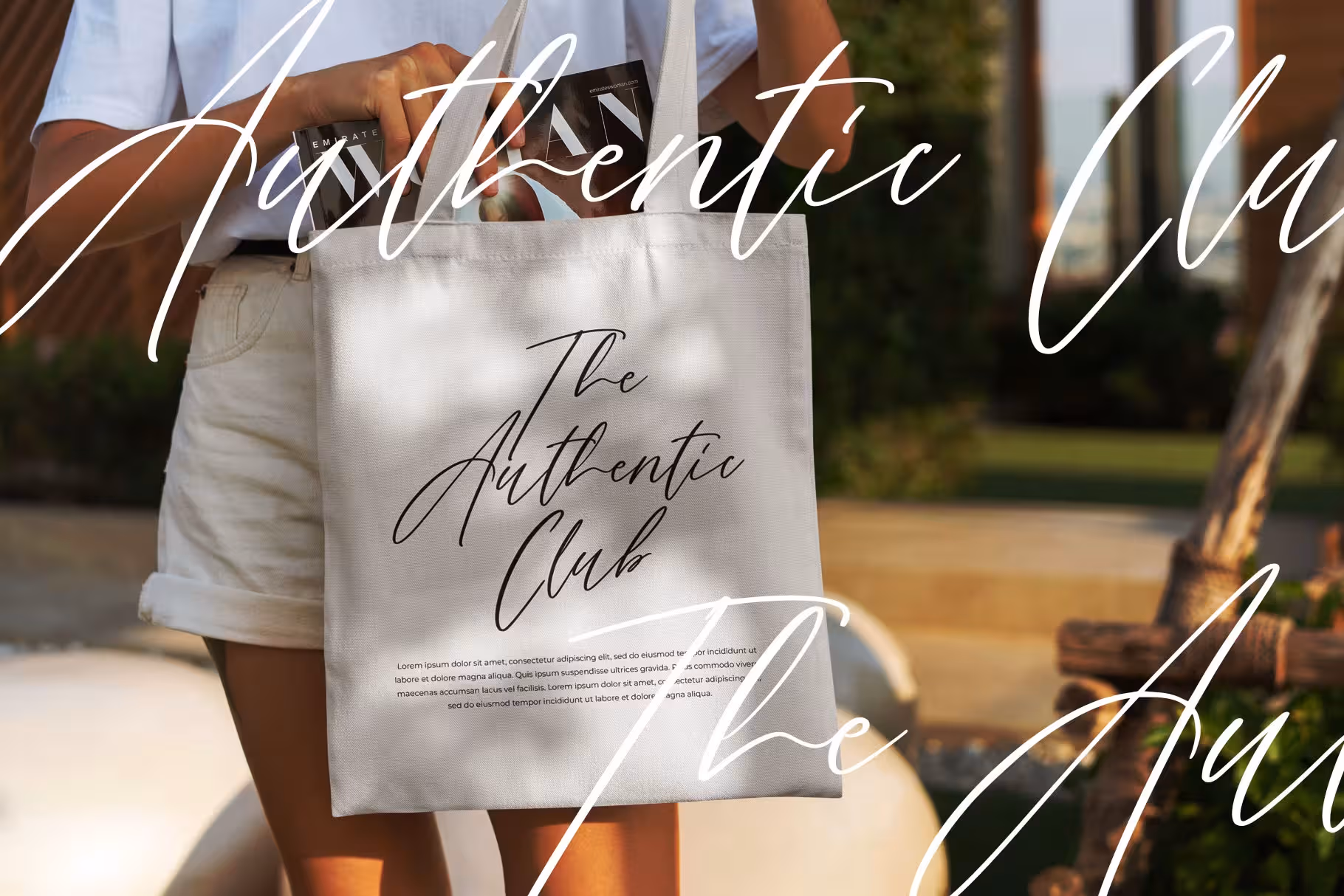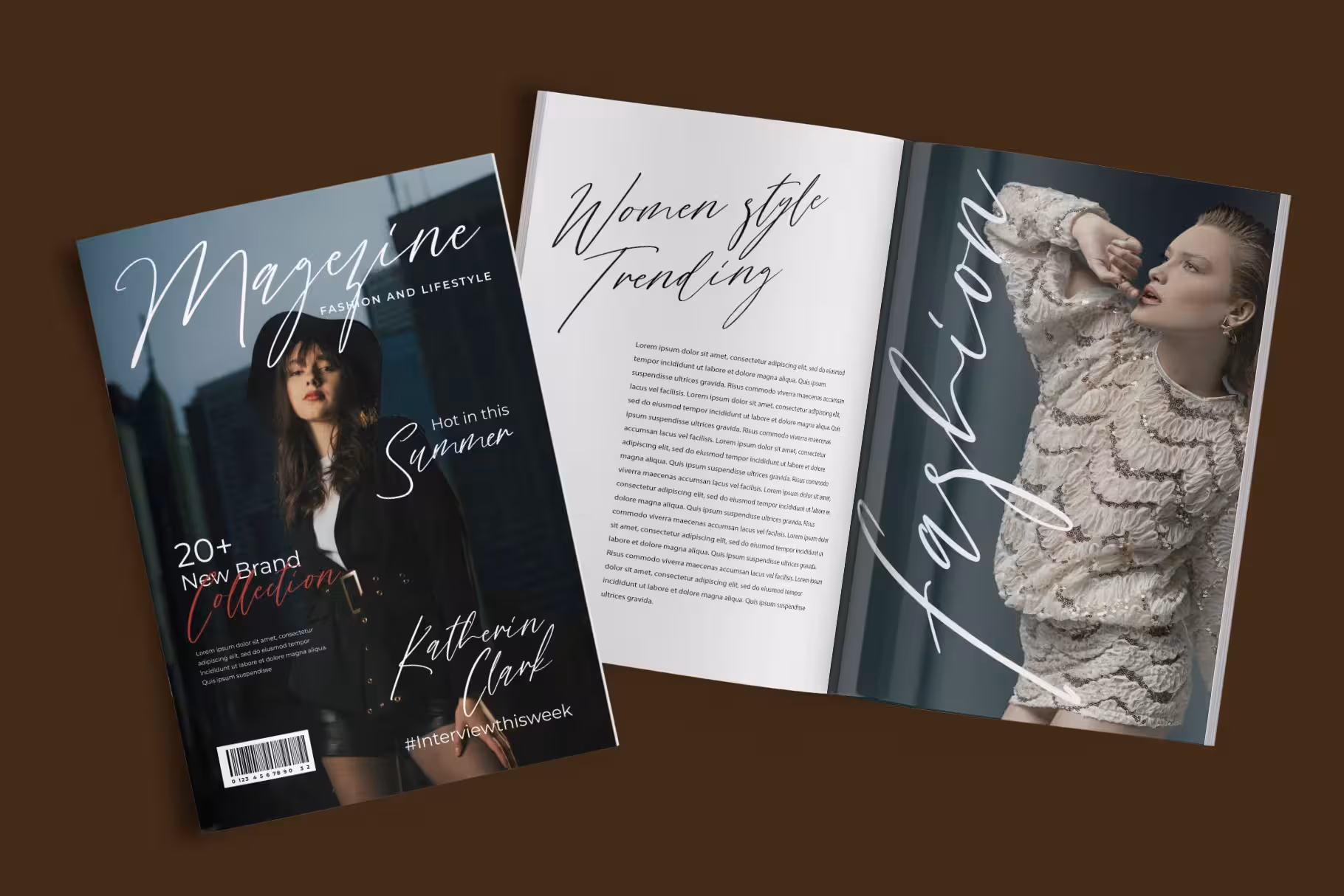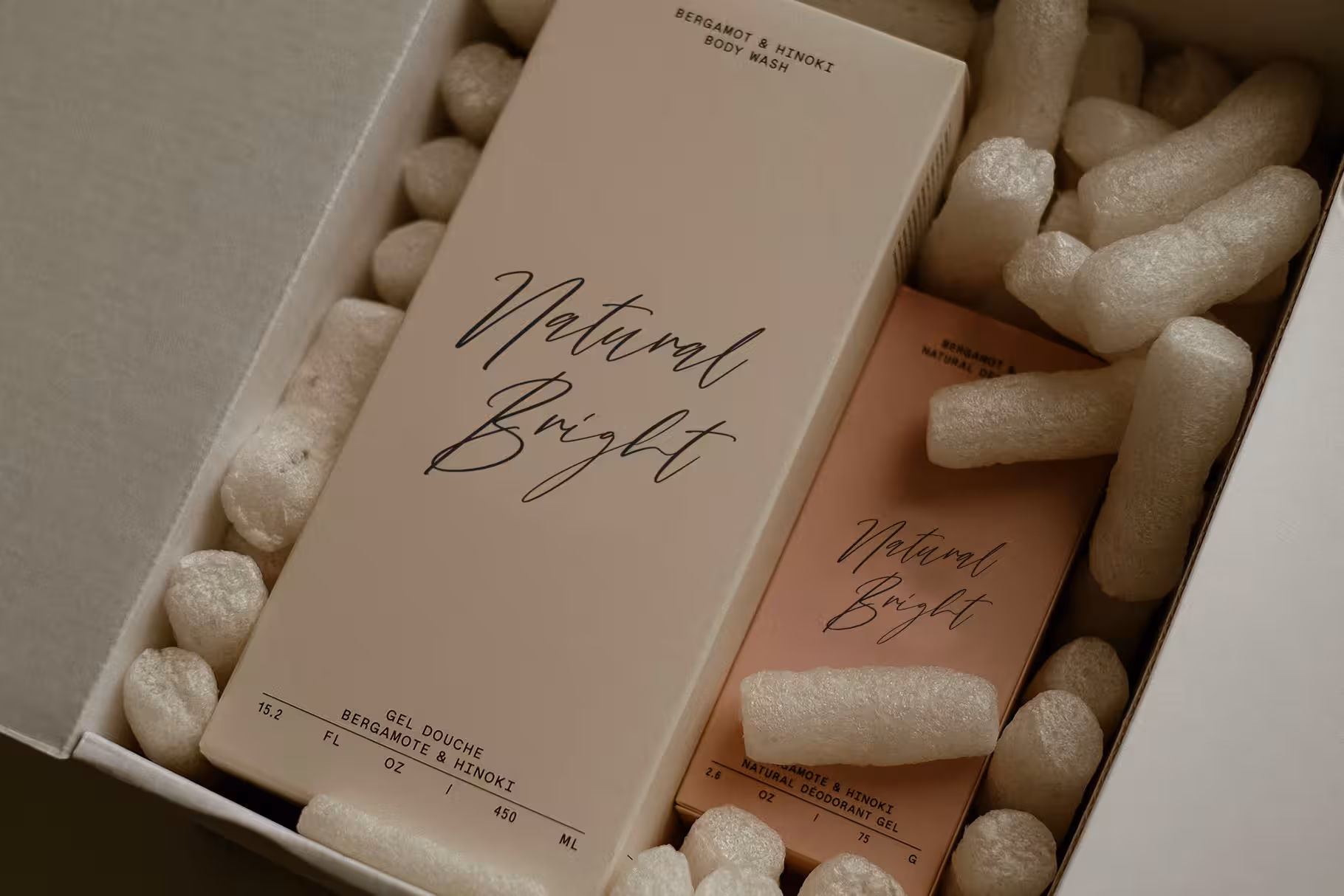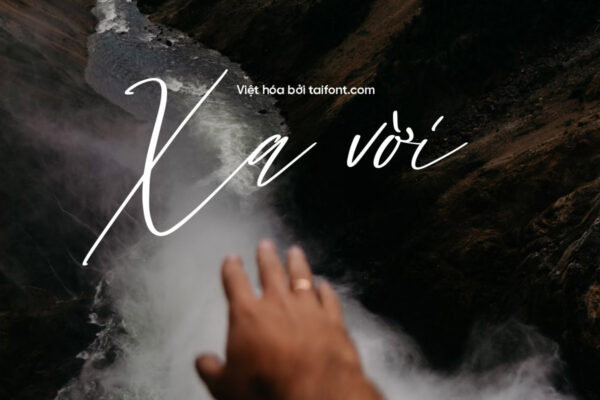
Giới thiệu về Font TF Methonia Việt hóa
TF Methonia Việt hóa là một font chữ viết tay (script font) nổi bật với những đường nét thú vị, phóng khoáng và đầy cá tính. Font này mang đến vẻ đẹp tự nhiên, duyên dáng và một chút ngẫu hứng, gợi cảm giác như một chữ viết tay được viết nhanh nhưng có hồn, tạo nên sự độc đáo và riêng biệt.
Với sự duyên dáng và tính thẩm mỹ cao, Methonia là lựa chọn lý tưởng cho các thiết kế muốn truyền tải sự tinh tế, cá nhân hóa và một chút nghệ thuật:
- Thiết kế tạp chí: Hoàn hảo để sử dụng cho các tiêu đề phụ, lời dẫn, trích dẫn hoặc các bài phỏng vấn trong các tạp chí về thời trang, phong cách sống, nghệ thuật hoặc du lịch. Nét viết tay của Methonia sẽ làm cho nội dung trở nên sống động, gần gũi và thu hút độc giả.
- Thiết kế thư mời: Lý tưởng cho các loại thư mời sự kiện, tiệc tùng, khai trương hoặc thiệp mời cá nhân. Font này giúp thư mời trở nên sang trọng, cao cấp và đầy tính nghệ thuật, truyền tải sự trang trọng và độc đáo của sự kiện.
- Thiết kế cá nhân, blog: Phù hợp cho các blog cá nhân, nhật ký online, hoặc các ấn phẩm mang phong cách riêng, tạo cảm giác gần gũi, chân thực và đầy cảm xúc.
- Thiết kế thời trang, mỹ phẩm (nhấn nhá): Có thể sử dụng cho các chi tiết nhỏ, lời tựa hoặc slogan cần sự mềm mại, nữ tính và tinh tế trong các thiết kế liên quan đến thời trang, làm đẹp.
Với TF Methonia Việt hóa, bạn có thể dễ dàng thổi hồn nghệ thuật, sự tinh tế và cá tính vào các thiết kế, tạo ra những sản phẩm không chỉ đẹp mắt mà còn đầy cảm xúc và sức hút đặc biệt.